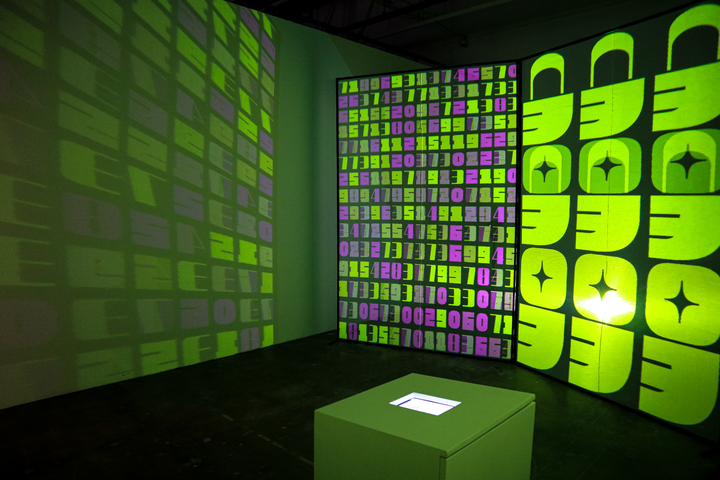
[서울=뉴시스] 박현주 미술전문 기자 = “전시, 보기만 하세요? ‘글멍’도 해보세요”
‘멍때리기’의 신선한 발상으로 마련된 ‘글멍테라피’ 미디어 퍼포먼스 전시가 열렸다.
서울 동대문 DDP 뮤지엄 3층 둘레길 갤러리에서 열리고 있는 전시는 제목부터 유쾌 발랄하다.
‘꼴값쇼: 뚱니버스, 다음 세대 문자의 침공’. 오감으로 즐기는 엉뚱한 글자세계로 초대한다.
입구부터 화려하게 맞이한다. 강렬한 색 대비가 눈에 띄는 숫자들이 카운트되고 응원가처럼 들리는 숫자 세는 소리가 흘러나온다. ‘뚱니버스_글멍테라피’ 영상으로, 멍하니 글자를 바라보게 한다.
중앙의 대형 화면에는 가변 형태 폰트로 풀어낸 ‘뚱니버스_다큐멘터리’도 무한재생되고 있다.
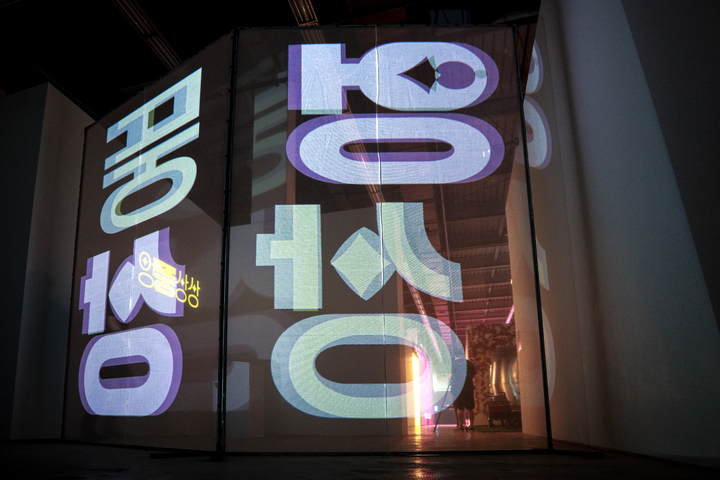
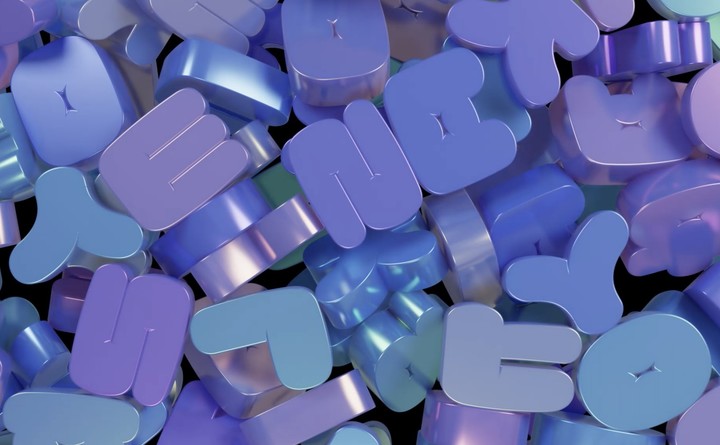
이 전시는 2019년 8월 윤디자인 30주년을 맞아 폰트라는 매체가 확장할 수 있는 영역이 어디까지 인지 알아보기 위해 시작됐다. 주인공이 되지 못한 폰트들의 애도와 찬사이기도 하다.
전시를 기획한 엉뚱상상 스튜디오는 “’폰트도 주연이 되어보자’라는 접근으로 ‘꼴값쇼’ 프로젝트를 시작했다”며 “꼴값은 글자 꼴(Form)의 값(Value)을 재정의한 것”이라고 소개했다.
‘엉뚱상상 스튜디오’는 국내 폰트 시장을 석권하고 있는 윤디자인그룹에서 타이포 브랜딩 영역을 맡고 있다. 폰트를 읽고 쓰는 글자에 한정 짓지 않고 만지고 감각하는 놀이도구로 확장시키는 작업을 한다.